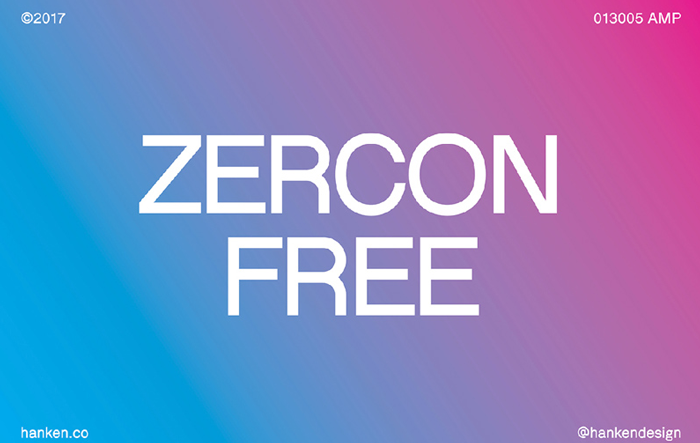
A fonte ‘HK Zercon Typeface’ é uma escolha perfeita para designers que buscam um tipo sans serif leve e versátil. Desenhada pelo famoso designer Hamilton, ela integra-se perfeitamente a várias aplicações gráficas como logotipos, cartões de convite, cabeçalhos em redes sociais, embalagens de produto e até mesmo painéis publicitários. Com seu formato sem serifas, HK Zercon apresenta uma elegância que parece ter sido escrita a mão, mas mantém-se simples e clara. Isso torna-a ideal para uso em qualquer aplicação visual onde precisa de legibilidade e simplicidade. Seja em um design minimalista ou um layout mais elaborado, ‘HK Zercon Typeface’ oferece um tom que combina perfeitamente com seu estilo clean, tornando-se uma fonte indispensável na sua coleção.